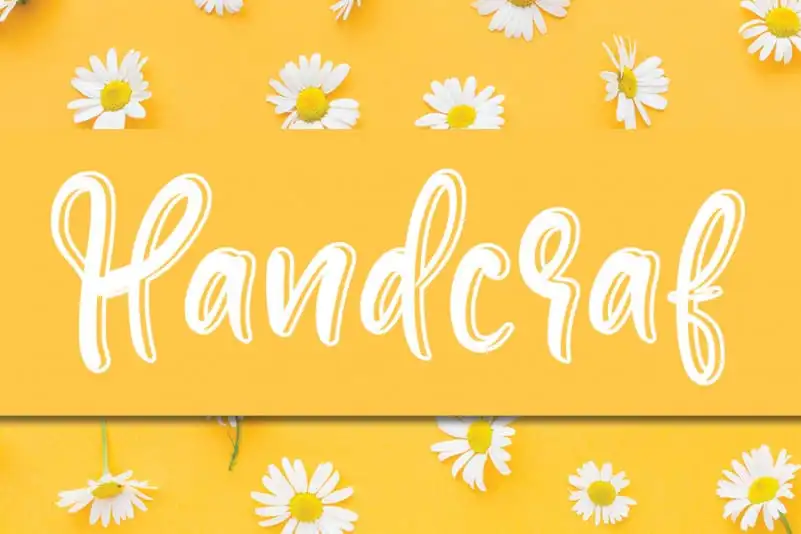
A fonte Handcraf Display Font é uma escolha perfeita para quem valoriza a criatividade na formatação visual dos seus projetos. A designer andikastudio criou esta fonte especial, destinada a oferecer uma experiência extraordinária aos usuários. Suas linhas finas e leves se combinam perfeitamente com formas mais volumosas, criando um equilíbrio elegante entre clássico e moderno. Com Handcraf Display Font em seu arsenal, você pode destacar seus textos de forma atraente em qualquer projeto que precise de uma pitada especial de personalização. Ideal para criações que exigem uma paleta de cores vibrantes e uma tipografia com um toque único de sofisticação. Não hesite em explorar Handcraf Display Font, ele é o companheiro perfeito para dar vida a seus projetos digitais mais criativos.